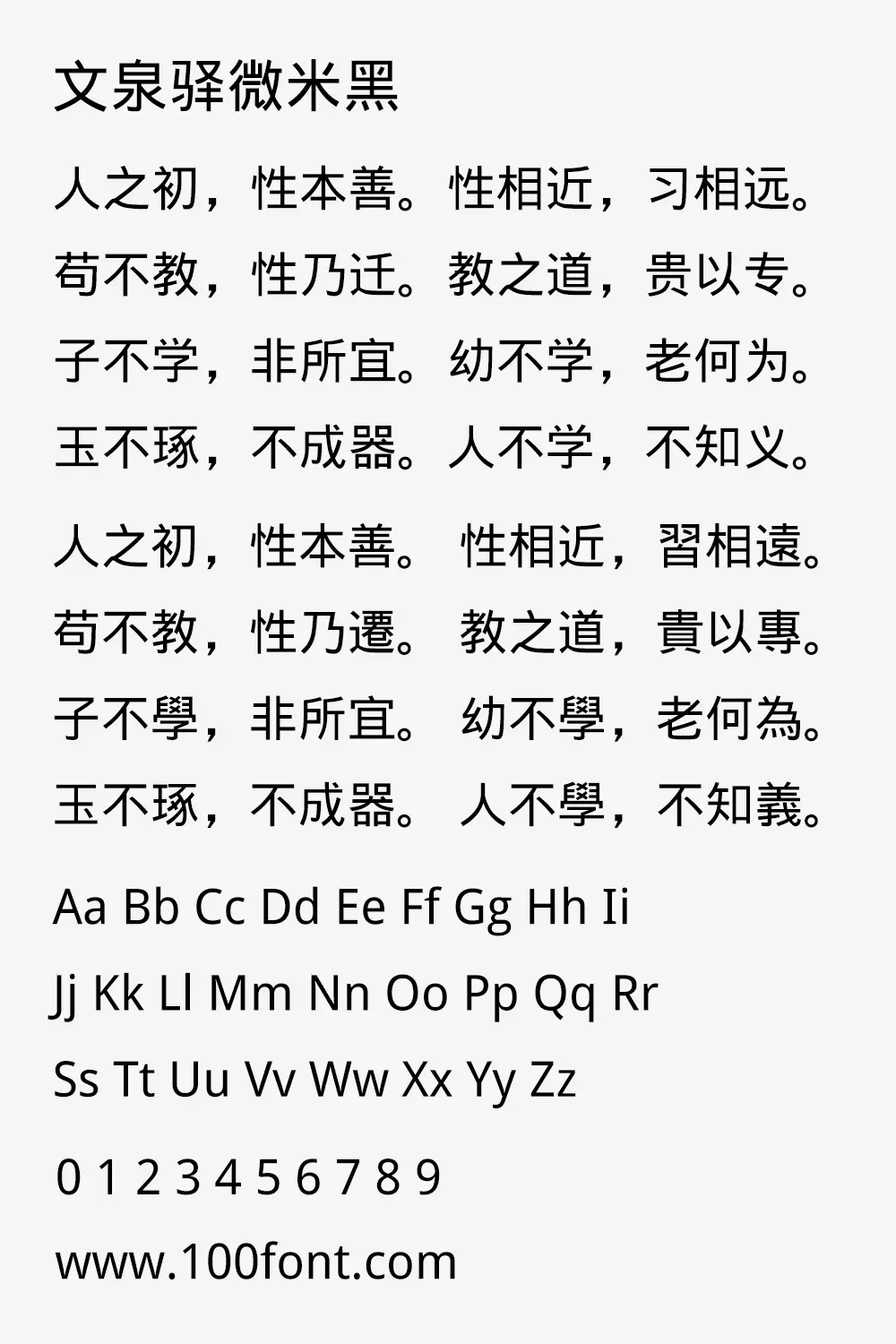
文泉驛微米黑是一個"自由字體"。該字體包含了所有常用簡體中文、繁體中文所需要的漢字(最新版本包含超過20932個漢字,完整覆蓋GB2312/Big5以及GBK標準字符集)。該字體同時還包含了日文、韓文和其他幾十種語言符號。以外,該字體還包含了高質量的Droid Sans拉丁符號和Droid Sans Mono等寬字體,並內置Hinting和Kerning信息。微米黑字體文件極小,特別使用於便攜式電腦設備。